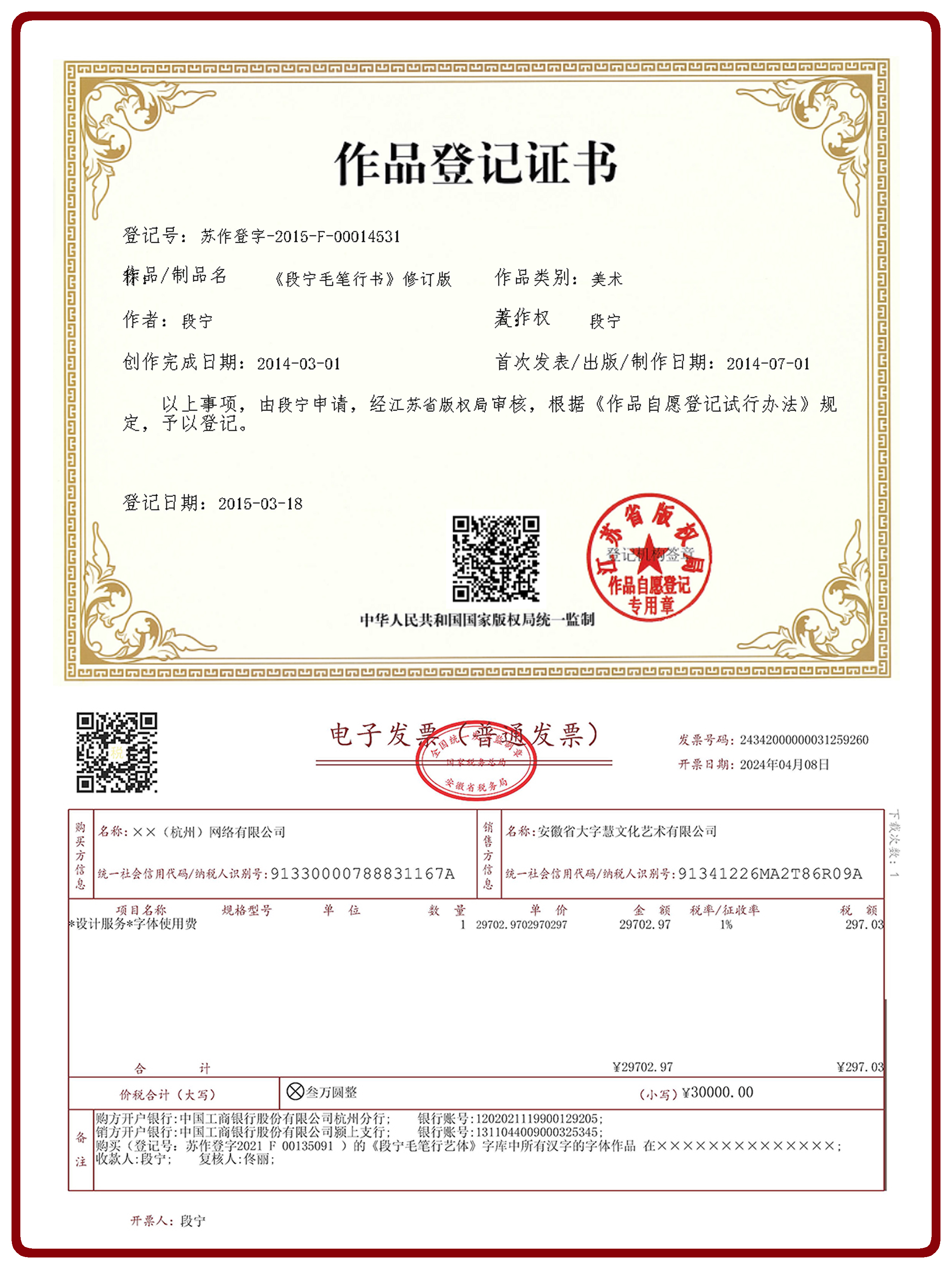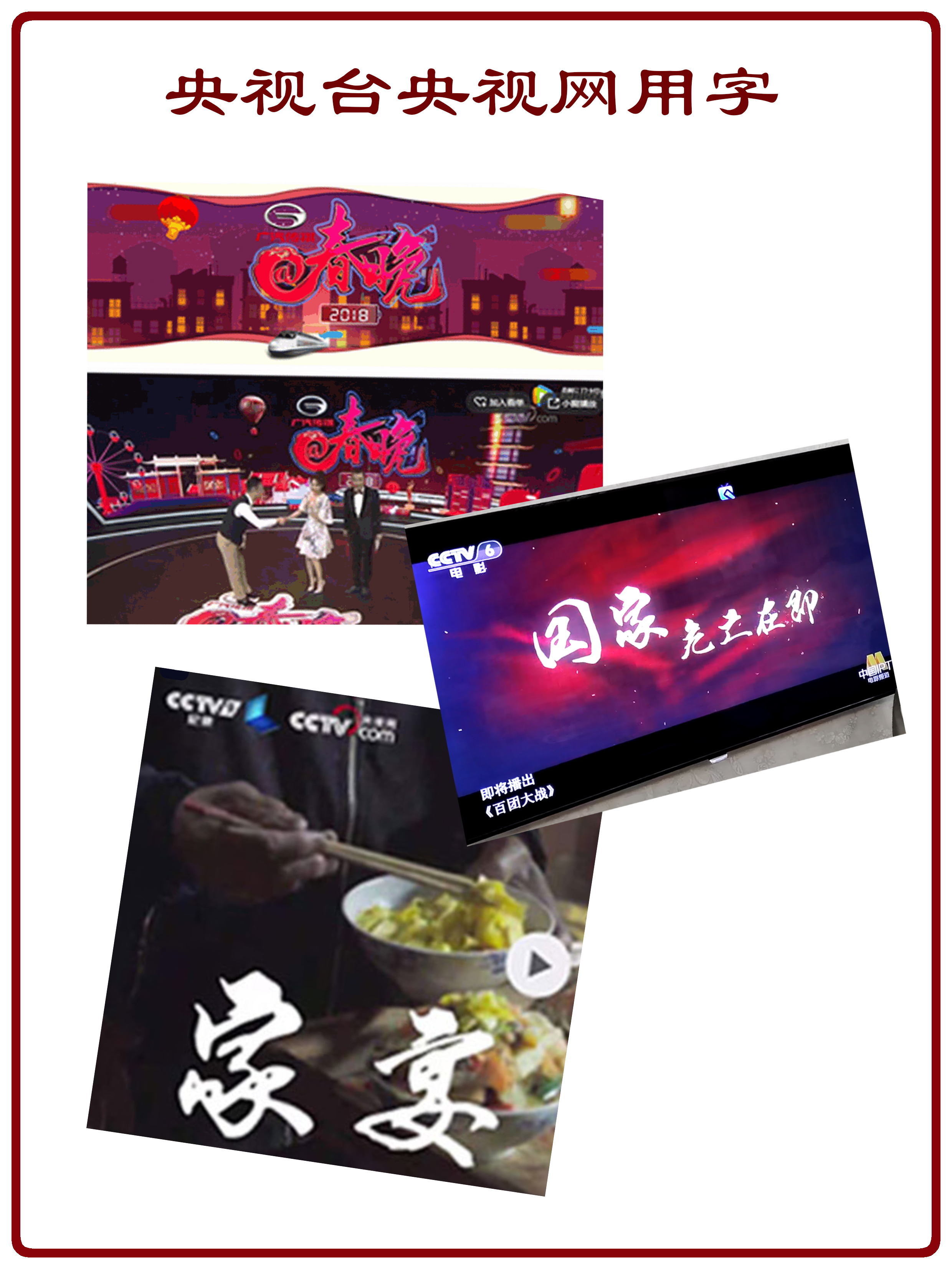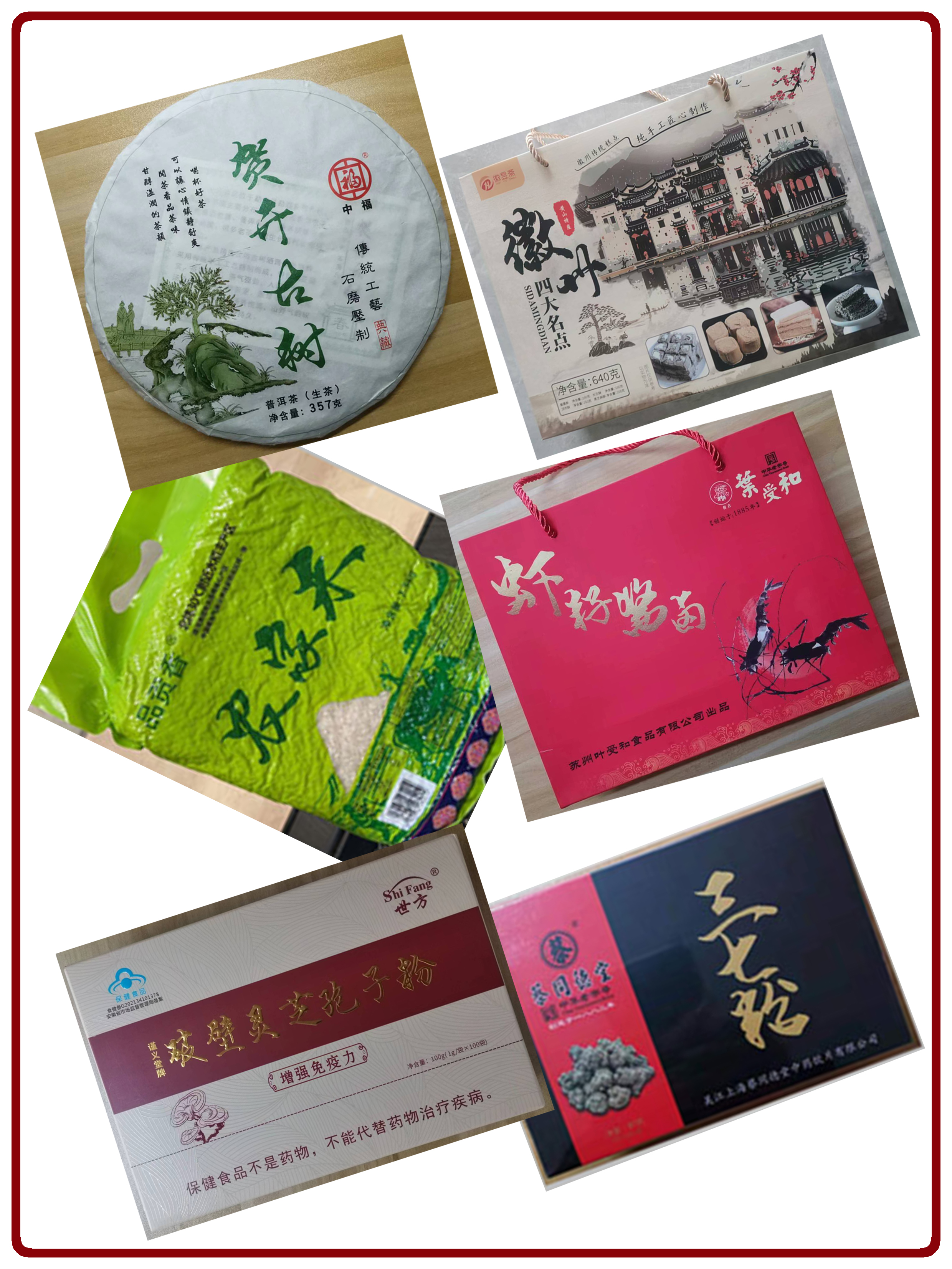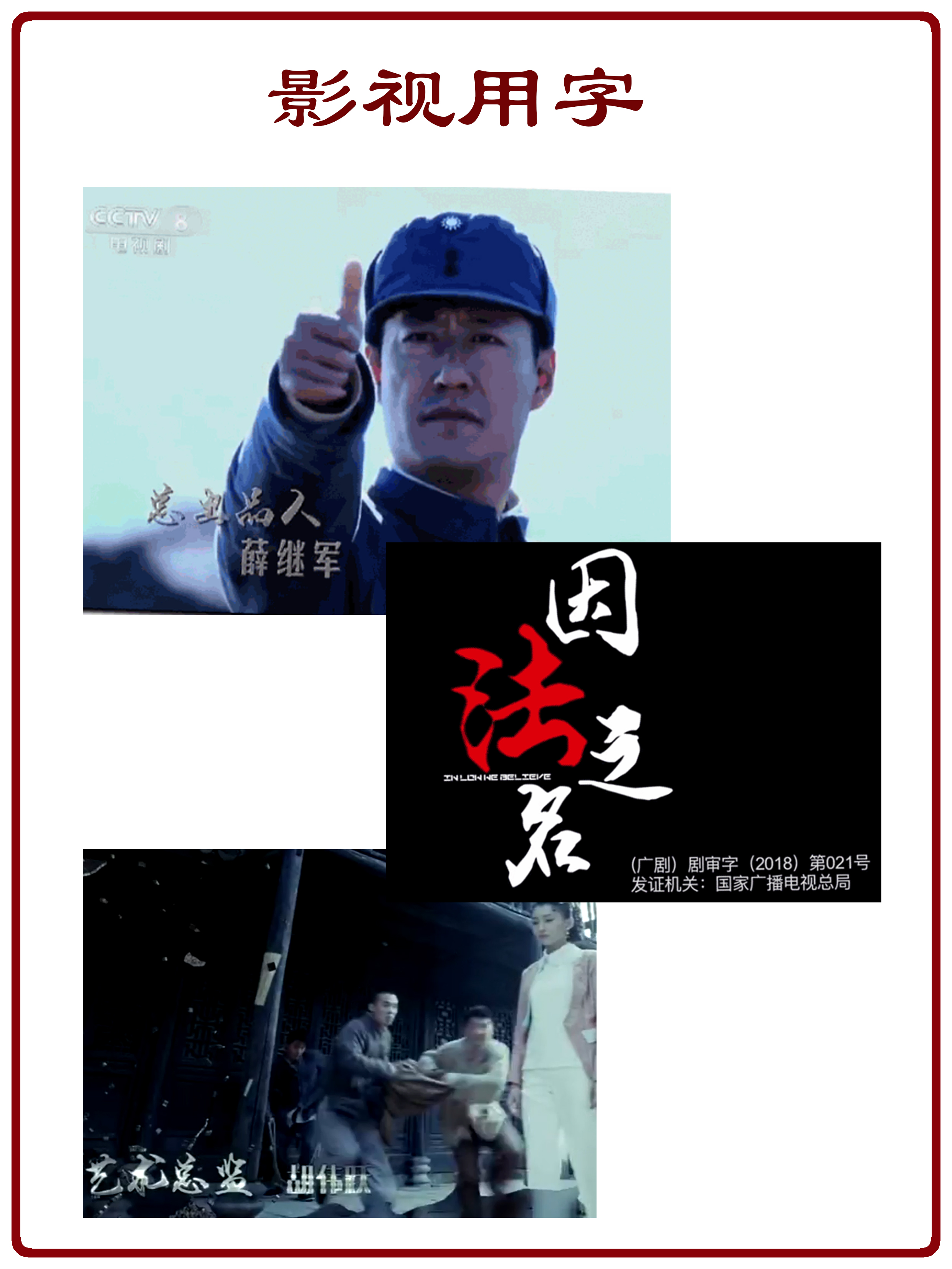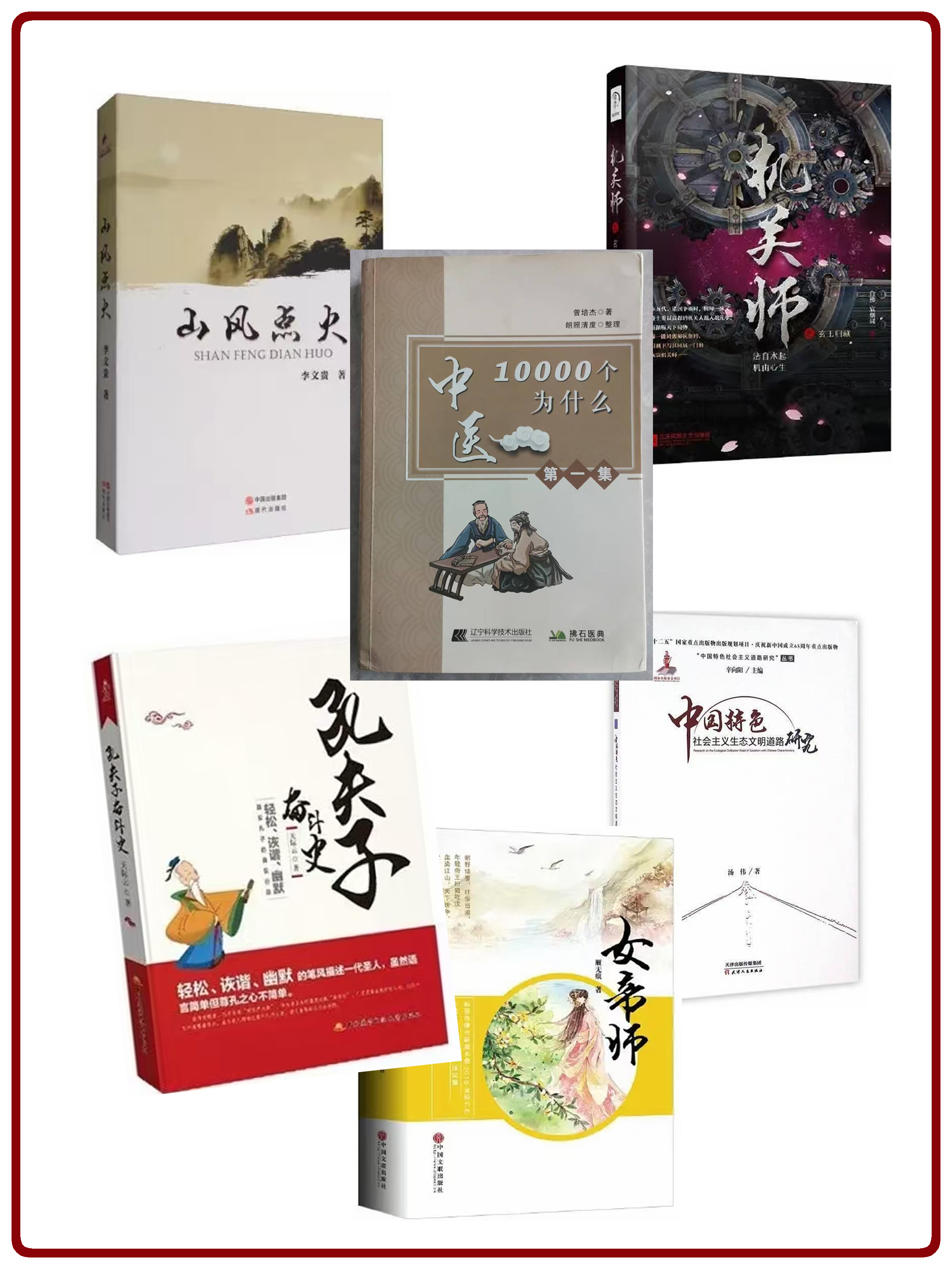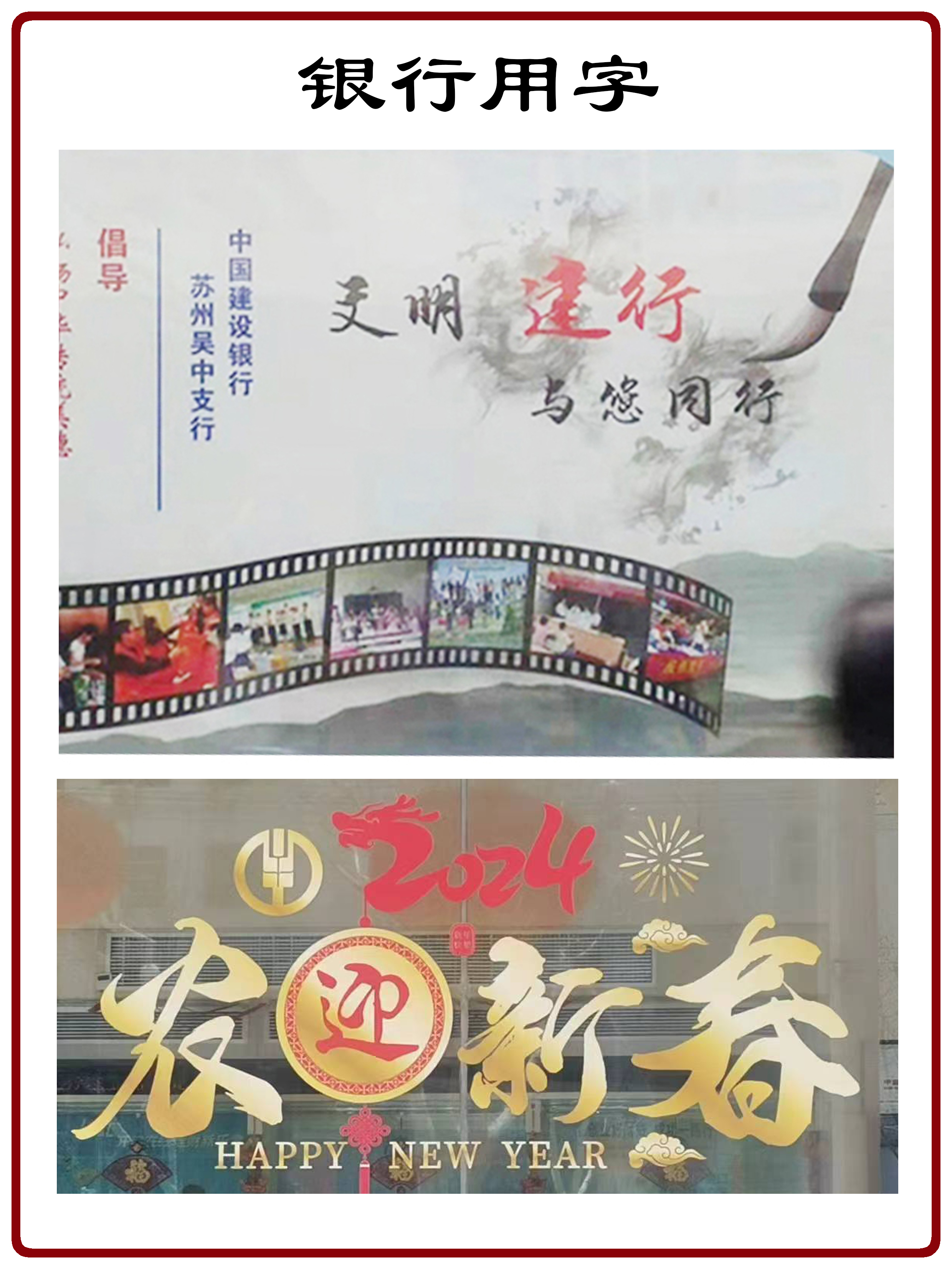
四十年笔墨凝一字
40年书法功底
段宁先生原创真迹
段宁先生亲笔书写,四十余年功底,原创有保证
段宁行书
流畅自然的行书风格,适用于标题和广告设计。
笔墨入屏,雅俗共赏:段宁毛笔行书字库的特征与流行逻辑
在数字设计与国潮审美并行的当下,书法字库早已脱离小众圈层,成为品牌视觉、媒体传播与日常创作的核心素材。在海量毛笔行书字体中,段宁毛笔行书始终保持着极高的市场渗透率:从央视网的栏目字幕到房地产的楼盘案名,从茶酒包装到文创商标,从企业 VI 到自媒体封面,个人设计师与各行业企业都将其作为高频用字选择。一款本土原创书法字库能跨越十余年仍保持生命力,既源于其本身扎实的笔墨功底与设计适配性,也离不开版权规范、场景兼容与文化趋势的多重加持。